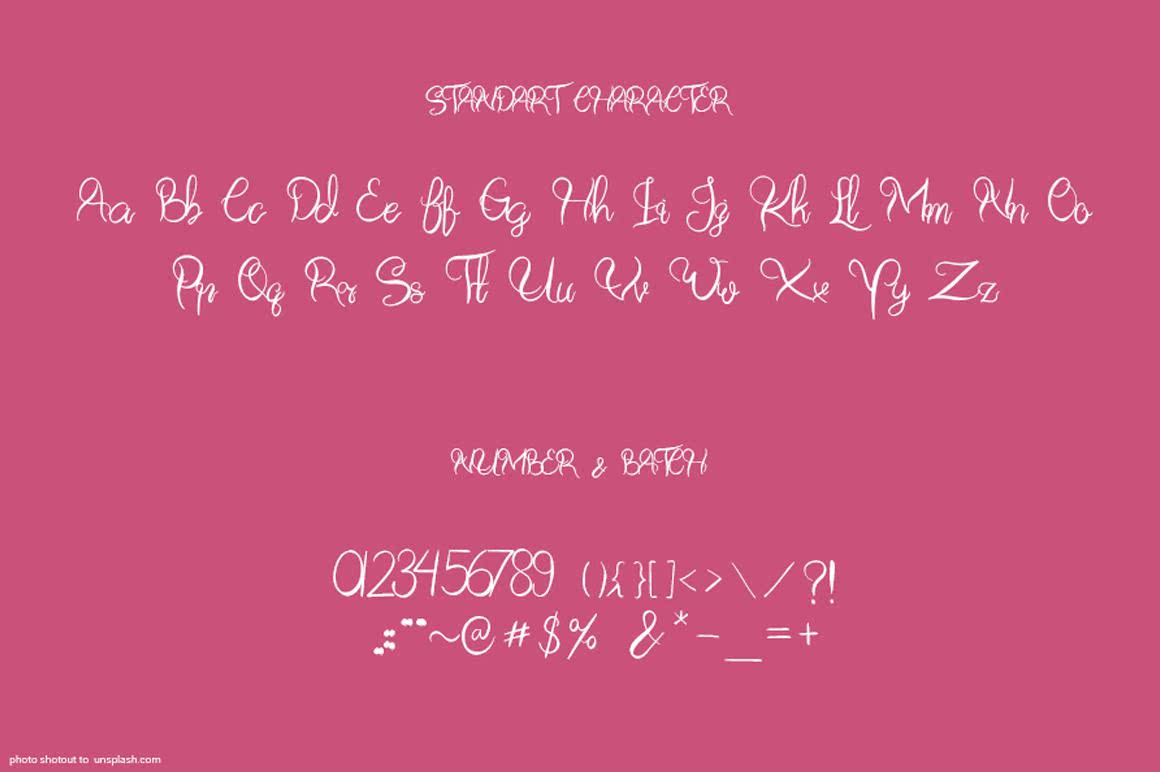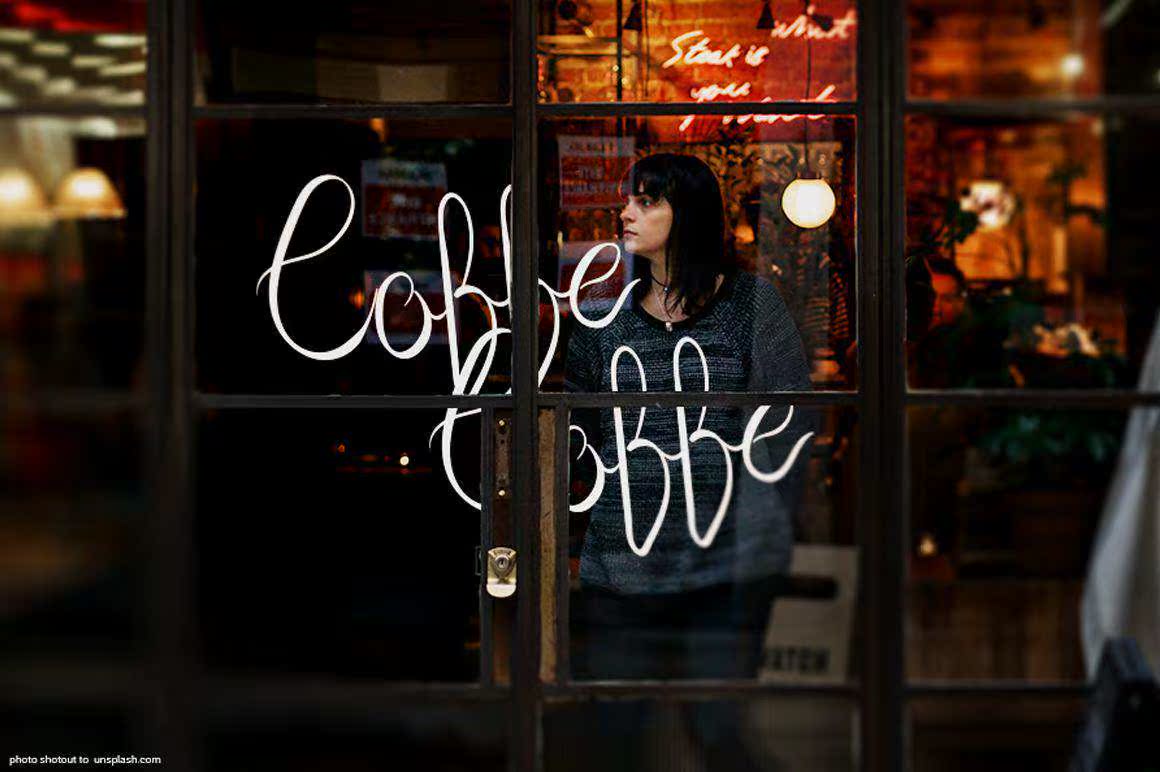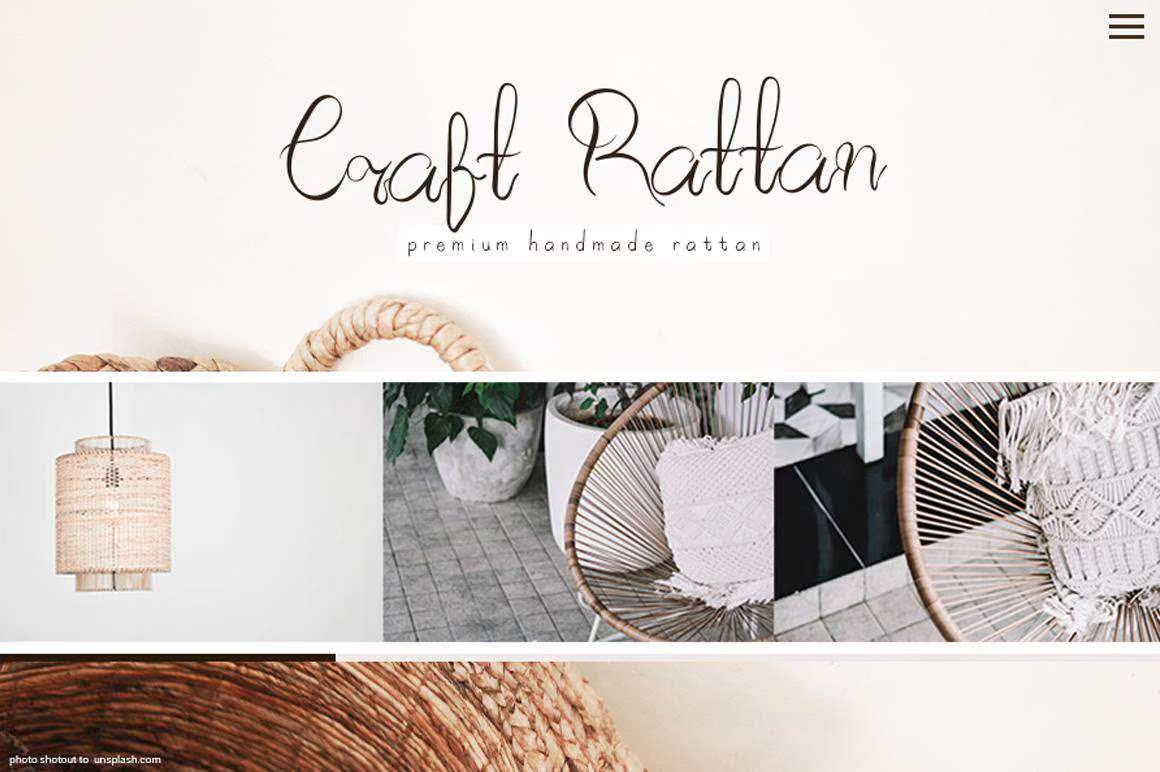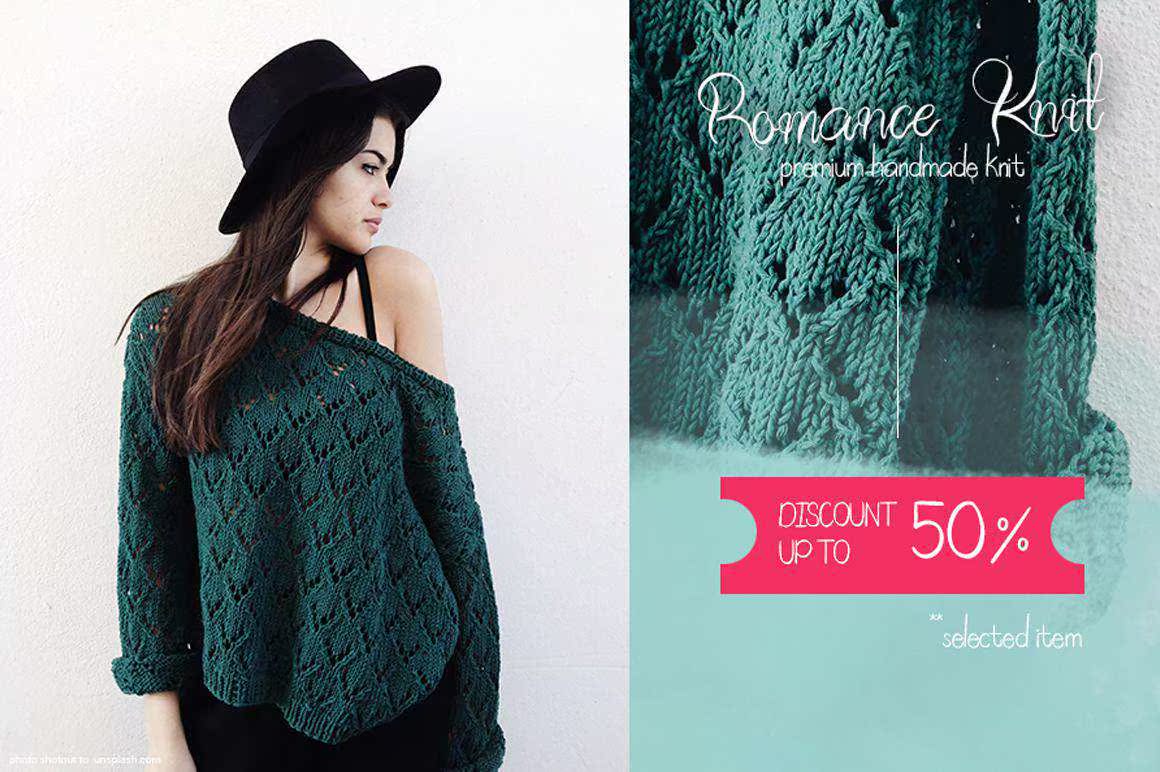
InnerBeauty是一款精致而永恒的手写字体。它是创建吸引眼球的徽标、品牌和报价的最佳选择。每个字体都有一个独特且美丽的外观,这将使您的设计变得生动!InnerBeauty是一款精致而永恒的手写字体。它是创建吸引眼球的徽标、品牌和报价的最佳选择。每个字体都有一个独特且美丽的外观,这将使您的设计变得生动!